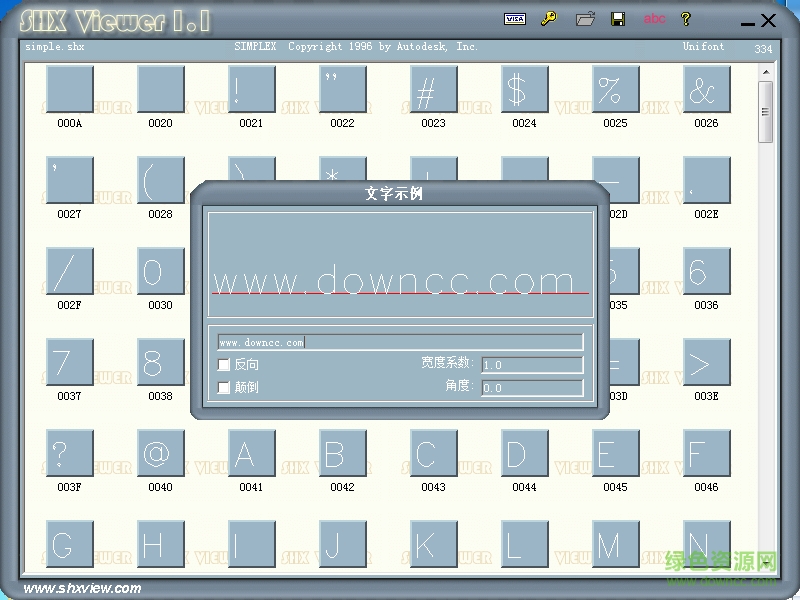
simple.shx是什么字體?simple.shx是一款非常簡單好用的cad字體,字體支持中英文輸入顯示,使用簡單能快速查看cad圖紙信息??靵砭G色資源網(wǎng)下載體驗(yàn)吧!
simple.shx是autocad的字體文件,一般在查看圖紙的時(shí)候如果使用了simple.shx字體而計(jì)算機(jī)中沒有它,則會無法正常顯示。